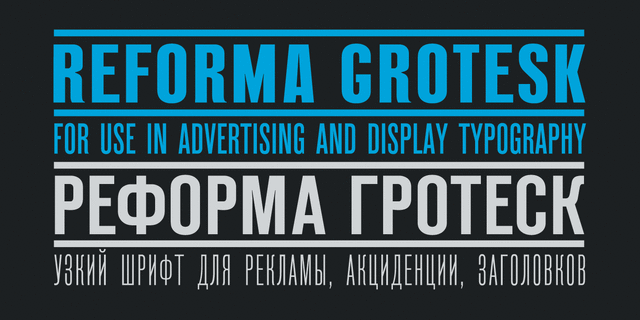
Гарнитура шрифтов Reforma Grotesk (Реформа Гротеск) разработана на основе рисунков дореволюционных шрифтов ручного набора Узкий Тонкий Гротеск, Полужирный Книжный Гротеск и Реформа словолитных заведений Лемана и Бертольда в Санкт-Петербурге. Это сверхузкий гротеск характерного рисунка, типичного для акцидентных шрифтов конца XIX – начала XX века, предназначенный для применения в рекламе и текстах небольшого объема. Шрифт награжден призом «Галина» за творческое исследование русской типографской традиции на международном конкурсе «Кириллица’99» в Москве. Дизайн разработан Альбертом Капитоновым, Выпущен компанией ПараТайп в 2000 году.
Ассоциации c начертанием Reforma Grotesk DemiКачества и характер:
громкий, важный, монументальный, высокий, твердый, устойчивый, мотивирующий, амбициозный, ровный, сжатый, статичный, серьезный, взрослый, городской, монотонный, стабильный, заметный, узкий, уверенный, четкий, рабочий, ответственный